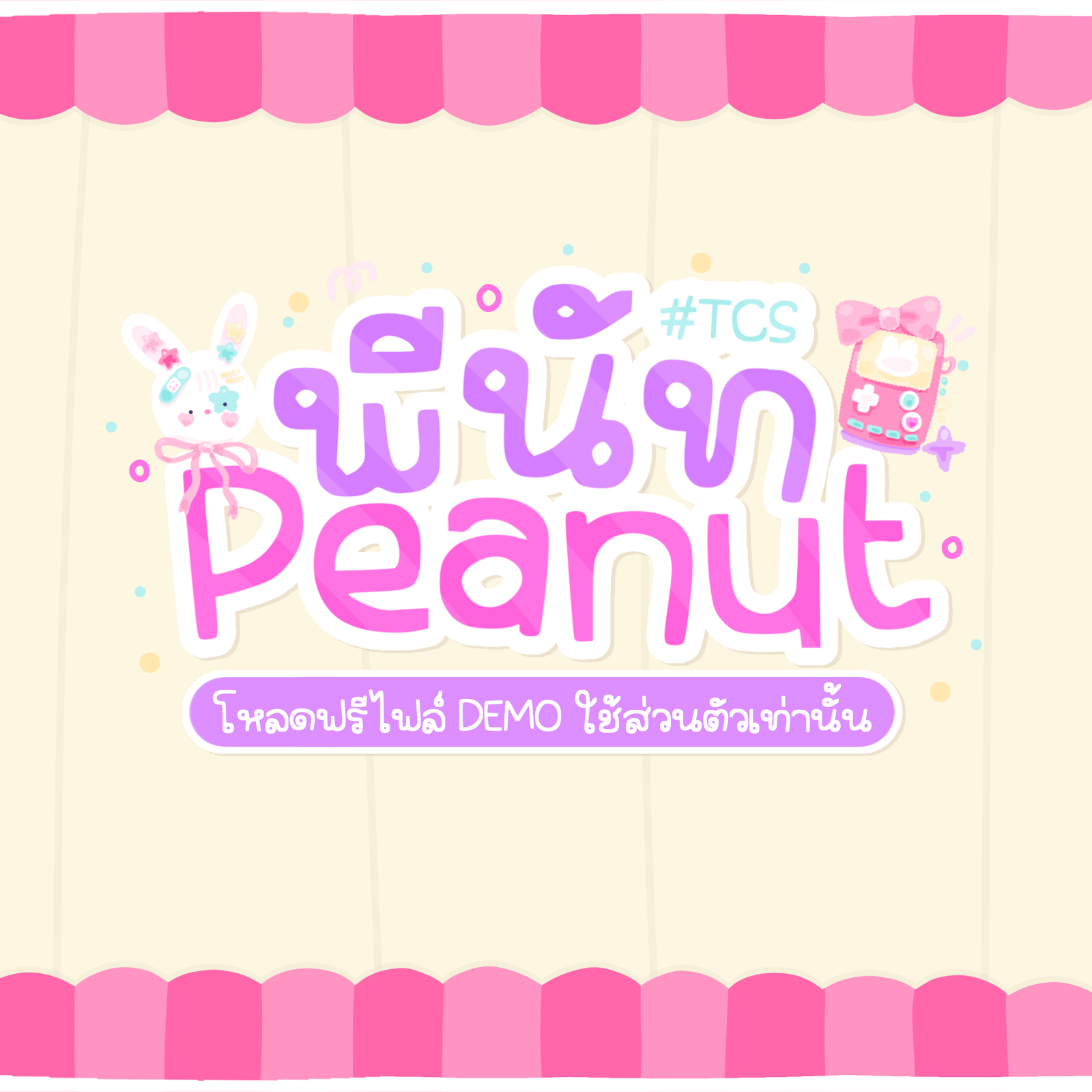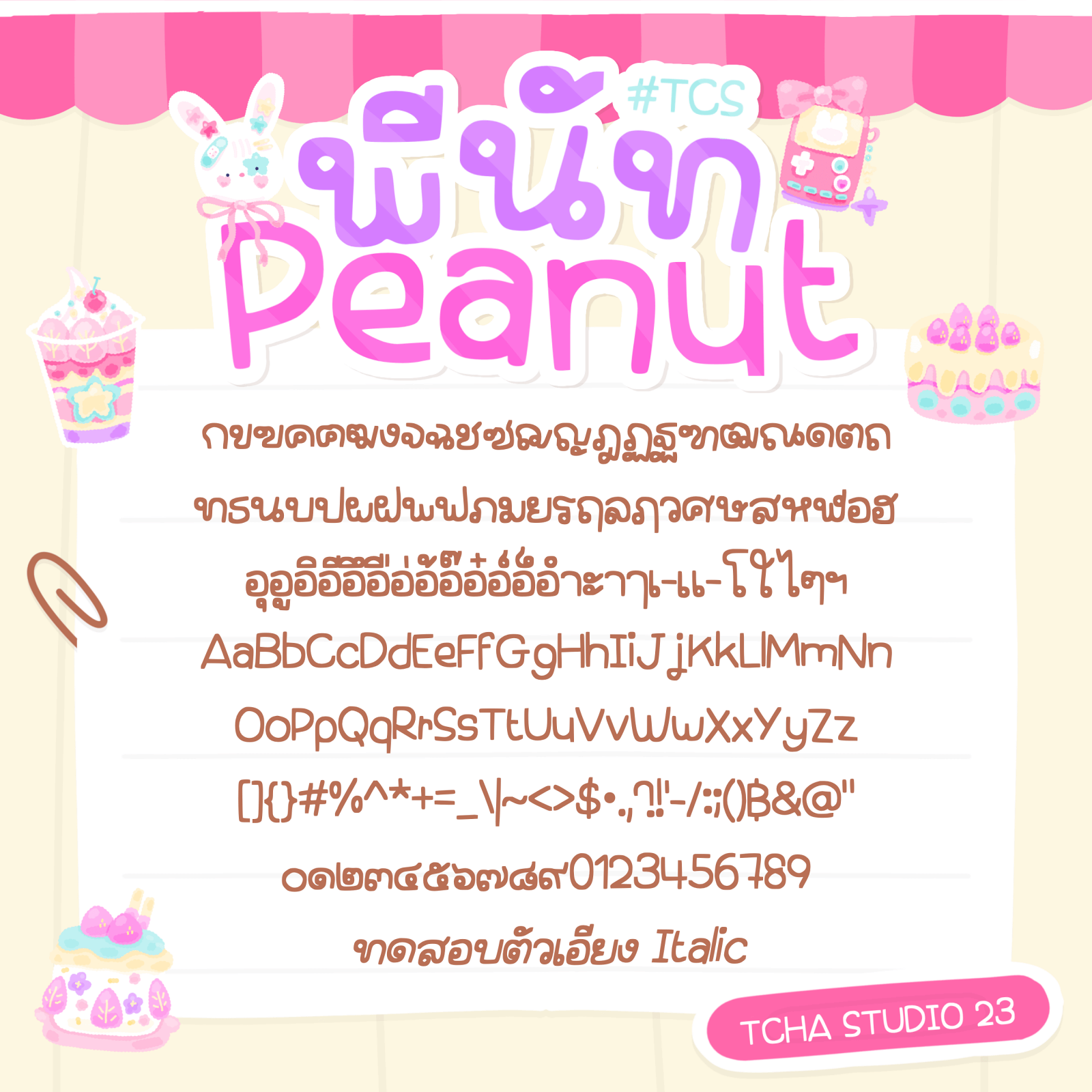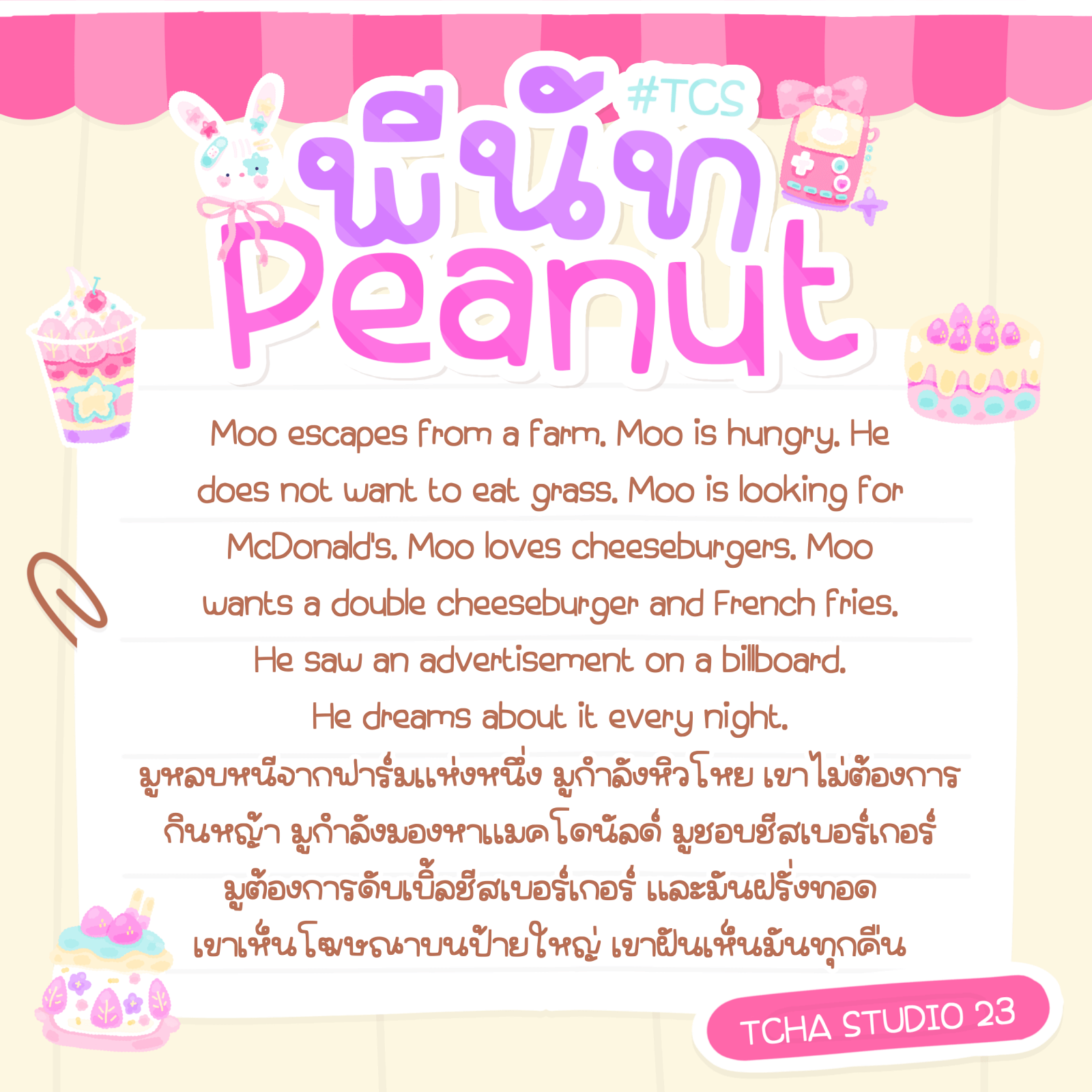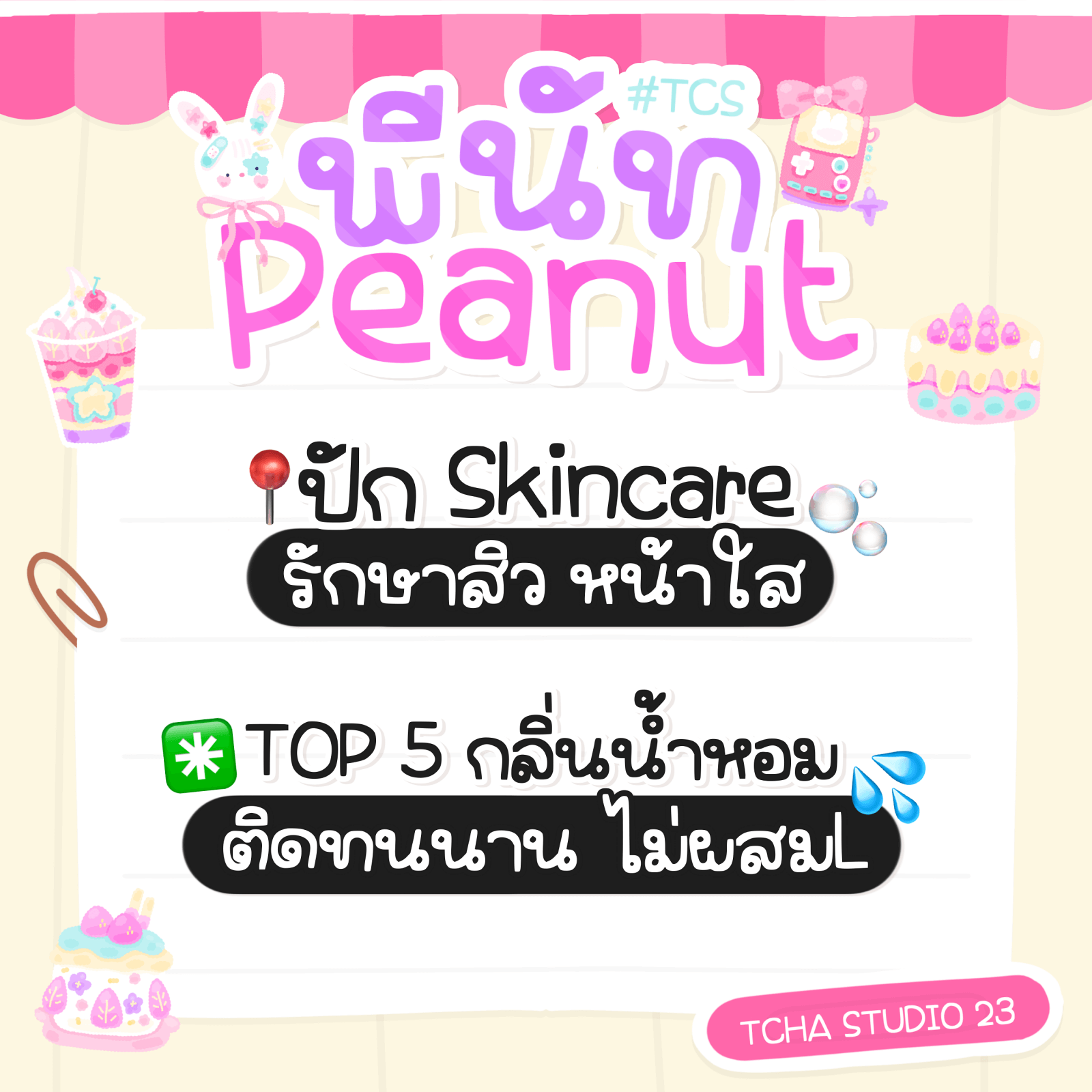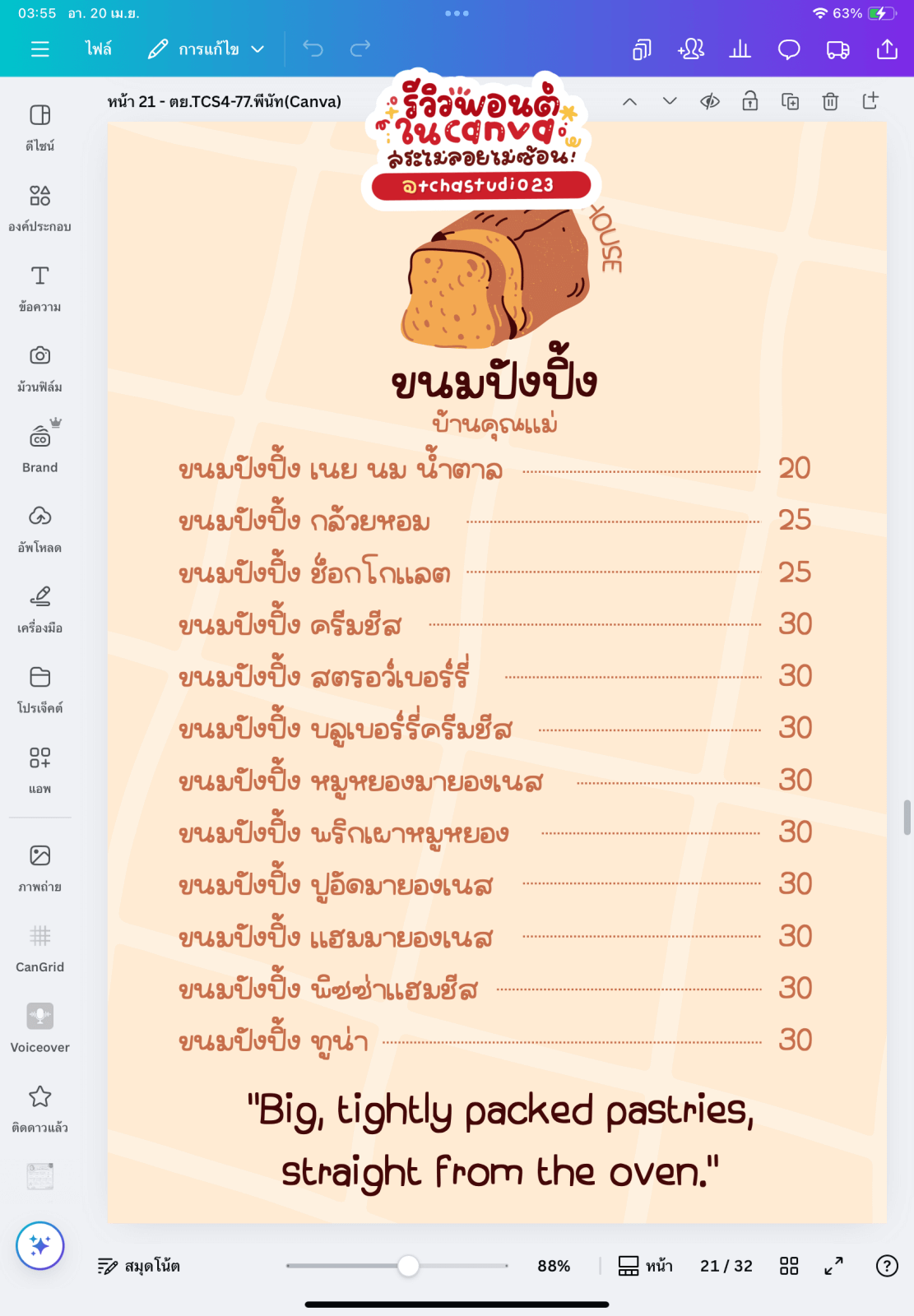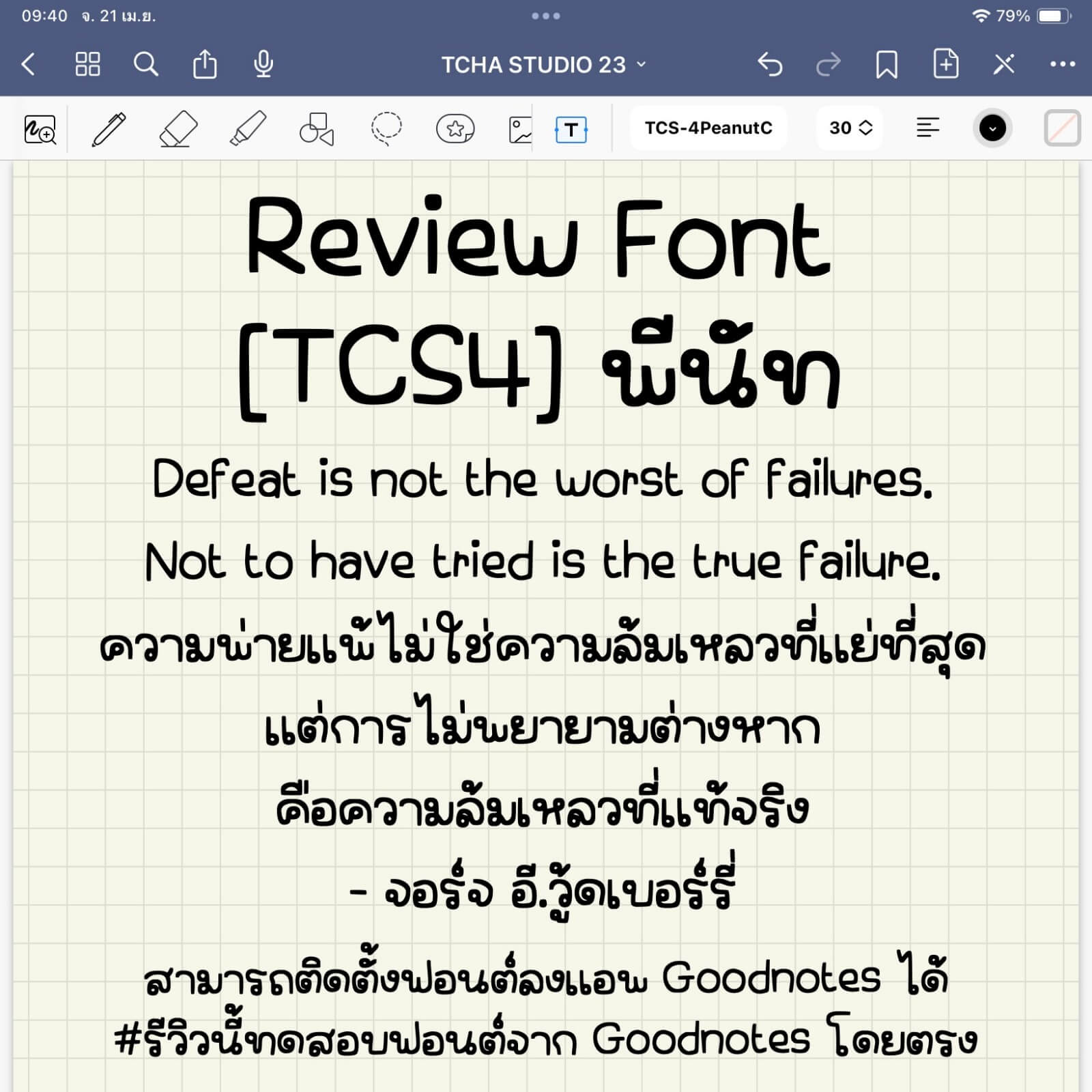
ฟอนต์พีนัท (TCS4Peanut) บรัชแบน ทรงเหลี่ยม ไม่ใช่แนวอ้วนกลม
– ไฟล์เวอร์ชันทดลอง (Demo) ยังไม่ปรับสระ มีน้ำหนักไม่เท่ากัน
ฟอนต์ : ฟอนต์พีนัท (TCS4Peanut)